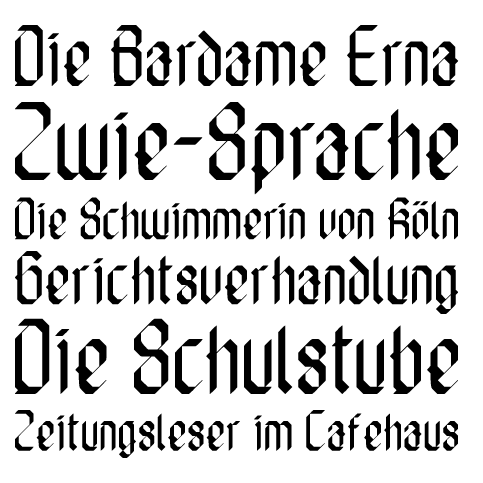
Ich weiß nicht ob ich lachen oder weinen soll … Hubbuch.
Äh ... Ist das so eine von diesen optischen Täuschungen ...?
Kann man da auch eine schöne Schrift sehen ...? :?
So kommen wir nun wieder zu Kathrin’s Law: Wo ist das ſ?
Schön ist sie nicht.